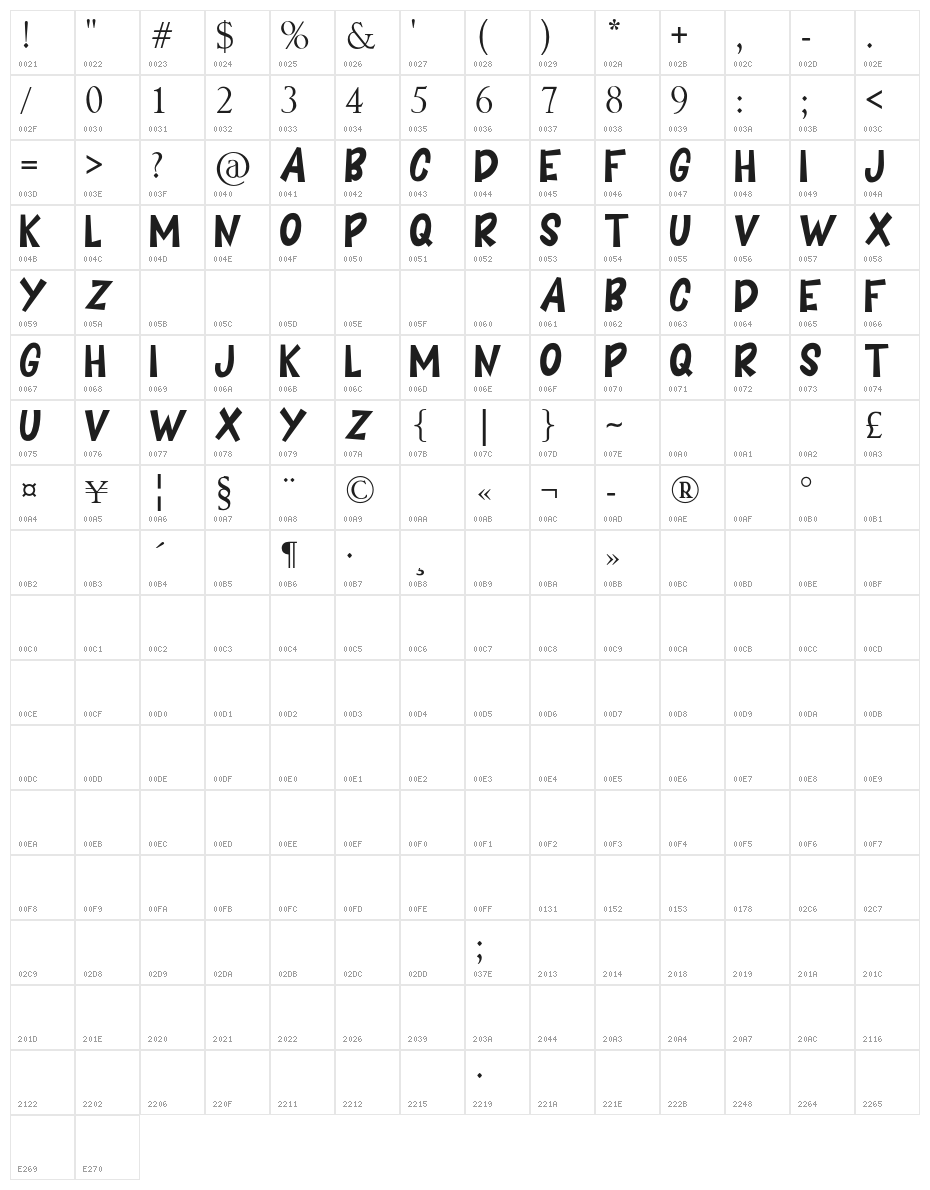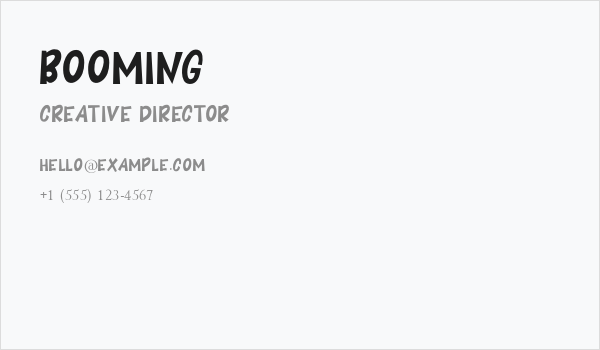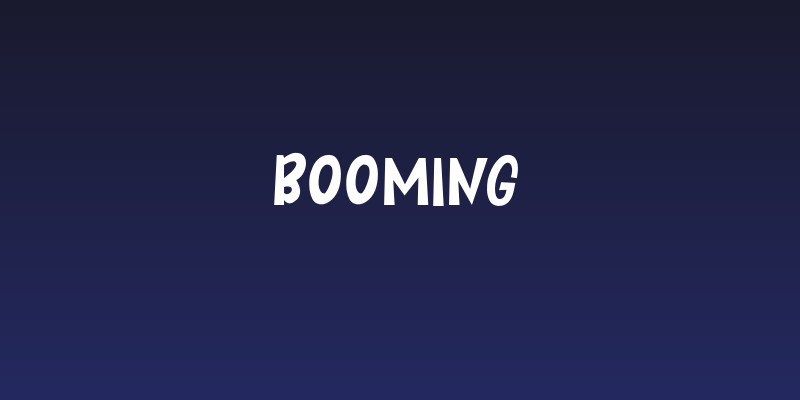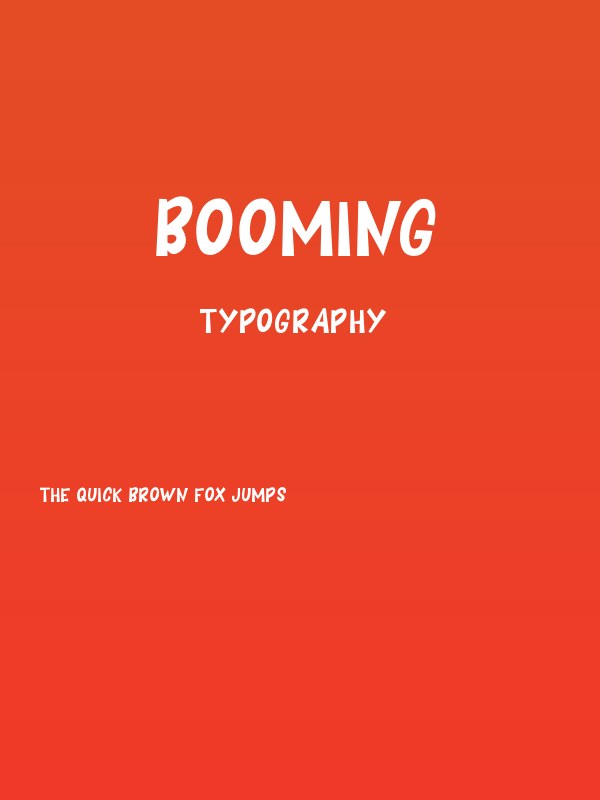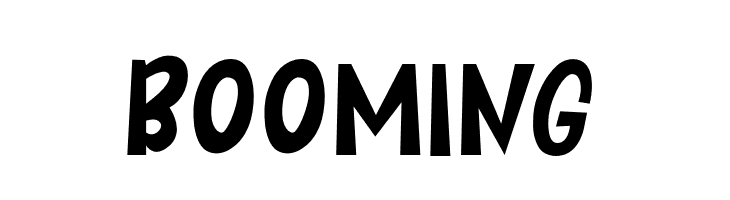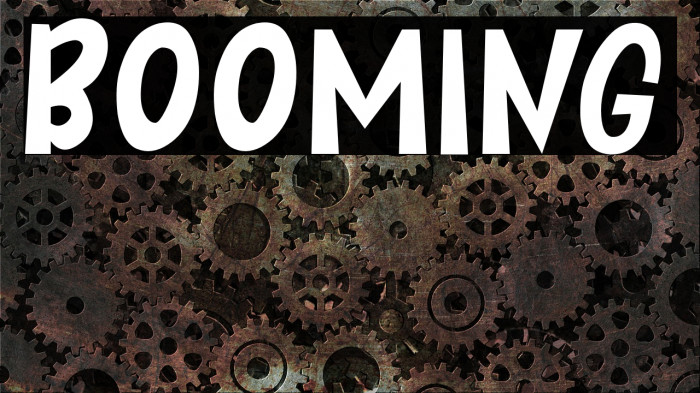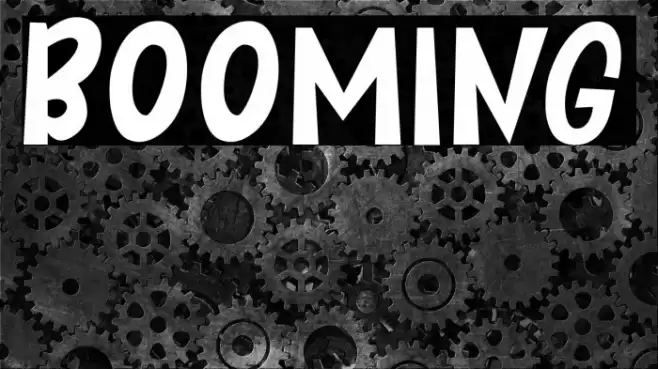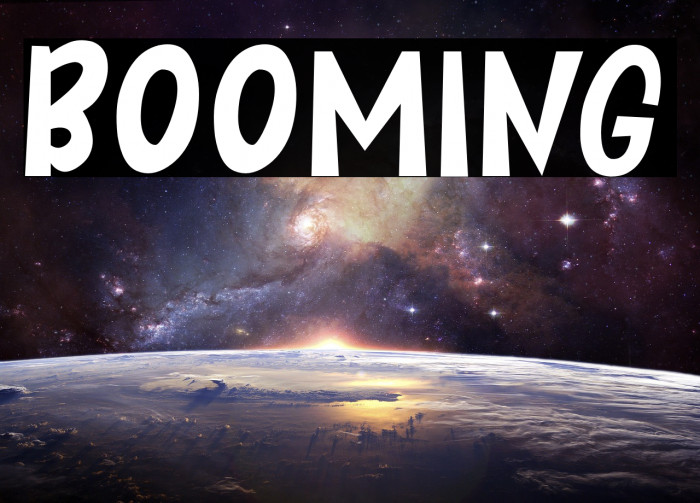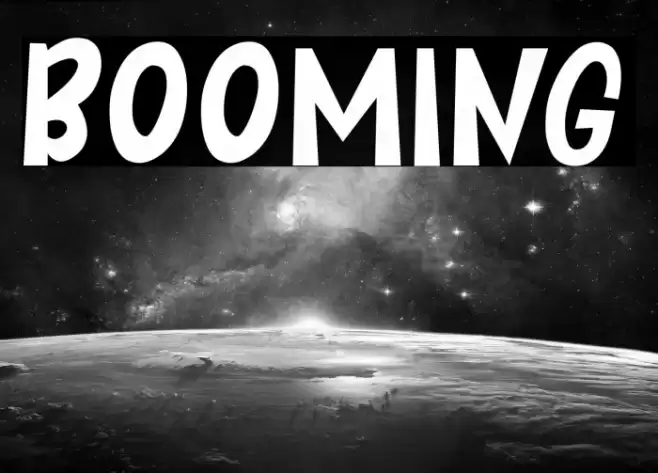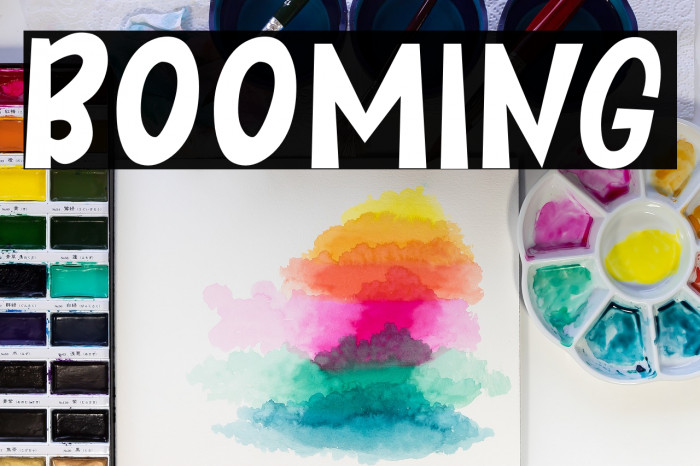
BOOMING Font
| समग्र शैली | Playful, Energetic, Hand-drawn |
| उपयोग का मामला | Headlines, Posters, Creative Branding |
| सुझाए गए प्रोजेक्ट | Ideal for children's books, playful branding, posters, and creative advertising. |